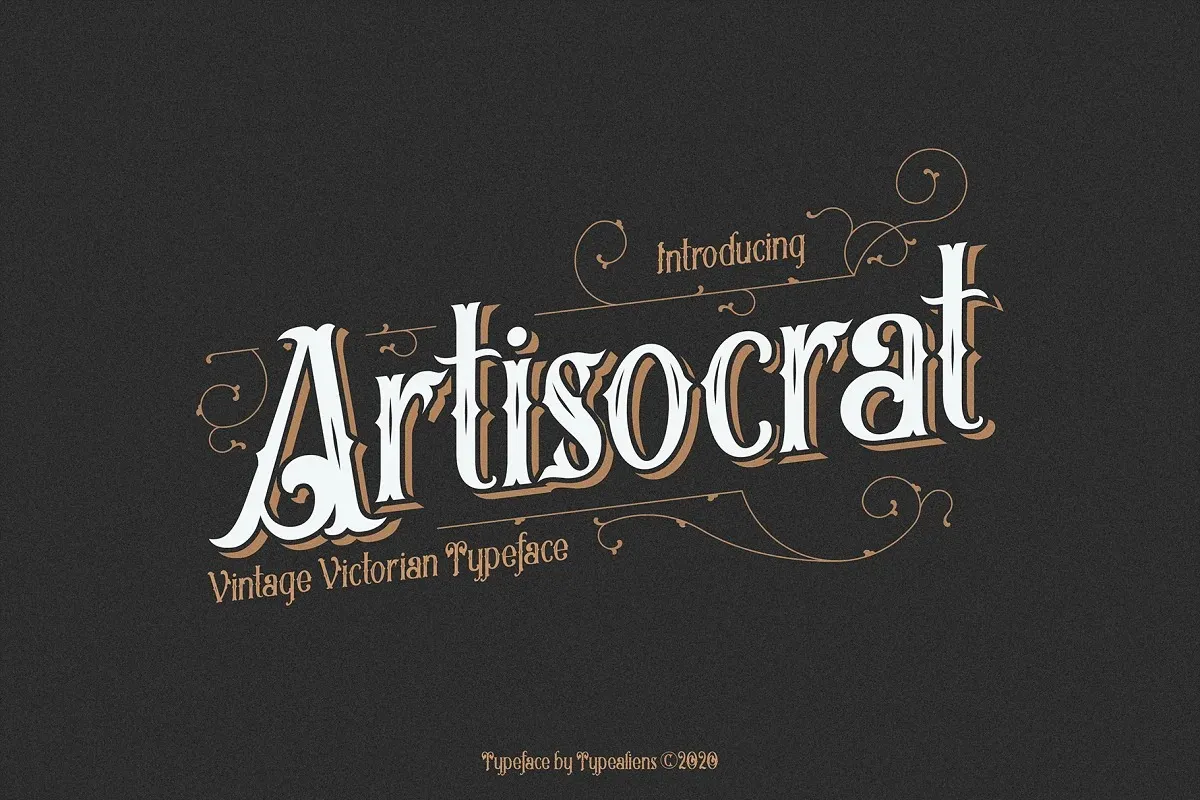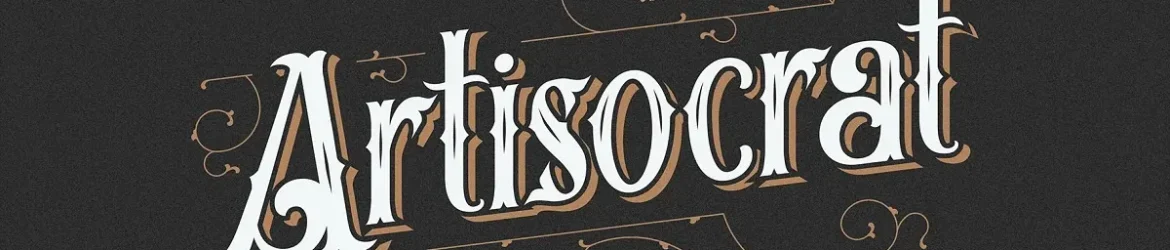
Esta fonte é perfeita para os amantes do design visual que desejam incorporar um toque elegante e clássico às suas criações. Inspirada nos selinhos de veículos dos anos 60 e 70, essa Display Font oferece uma aparência vintage com um ar sofisticado, ideal para ilustrações que vão do design de logotipo ao rótulo de cervejas ou até mesmo à designação de identidade corporativa. Seu design é perfeito para destacar mensagens importantes e cria designs únicos e memoráveis. Combinando elementos dos anos 60 e 70, a fonte artisocrat traz uma atmosfera nostálgica que vai complementar seus projetos de design com sucesso. Esta opção de fonte é ideal para aqueles que buscam agregar um visual elegante aos seus trabalhos visuais modernos.